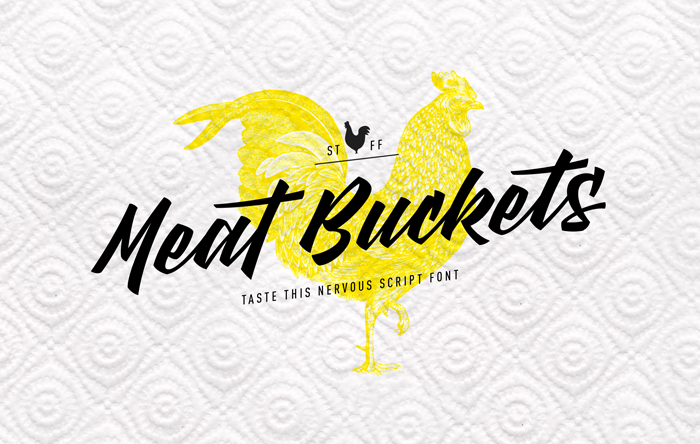
Introduzimos a nova Meat Buckets Font! Desenvolvida e compartilhada por StereoType, esta é uma fonte script nervosa com certa influência do estilo clássico. A Meat Buckets oferece uma experiência única no mercado de fonts, trazendo alternativas em número impressionante de 86, ligaturas contextualizadas e sublinhados para aprimorar ainda mais o seu potencial. Perfeita para um uso criativo em design gráfico ou impressão, esta fonte traz uma pegada vintage que certamente cativará designers e profissionais do setor. Uma escolha inteligente para aqueles buscando adicionar um toque único ao seus projetos de layout ou publicidade. Não perca tempo, a Meat Buckets Font é agora disponível em sua categoria Script Fonts!